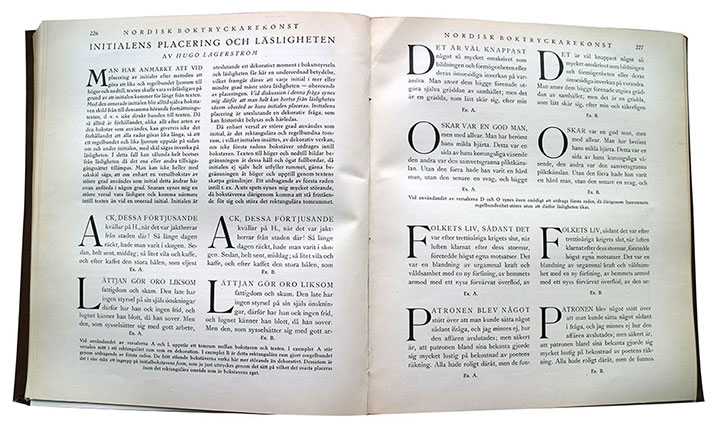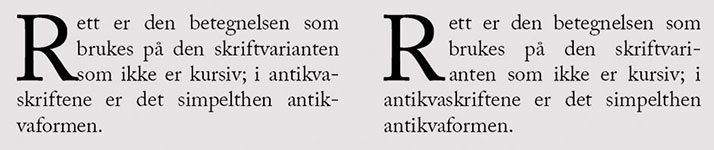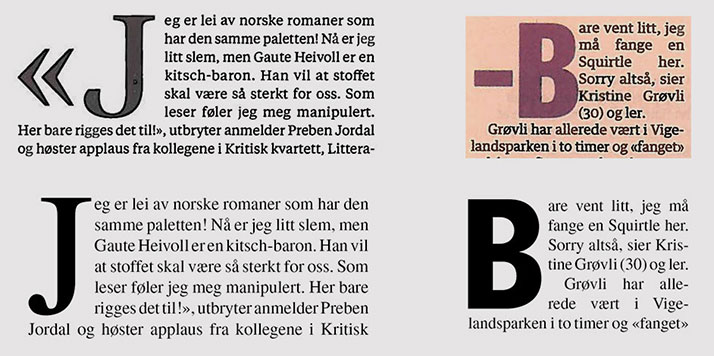
Initialer har vært anvendt i bøker lenge før Gutenberg og boktrykkerkunsten. De var ofte små malte kunstverk i de håndskrevne bøkene. Også i de første trykte bøkene ble disse utført for hånd av egne kunstnere eller håndverkere. Etter hvert ble det brukt typemateriell til initialer. Da oppsto det tvil om hvordan initial og tekst skulle knyttes sammen på en funksjonell og estetisk god måte.
Denne artikkelen vil ikke drøfte alle de vurderingene man kan gjøre seg om den typografiske formgivingen av initialer – også kalt begynnelsesbokstaver. Jeg har interessert meg for ett snevert forhold: hvordan initialen skal knyttes til resten av ordet/teksten som den tilhører. Skal den første linja trekkes nærmere initialen enn de etterfølgende? Jeg vil ta utgangspunkt i en strid i svensk boktrykkermiljø om dette omkring år 1920, der også praksisen i norsk boktrykk ble brakt inn i debatten.
Betydningen av dette spørsmålet vil noen avfeie som lite viktig, som «strunt» som noen uttrykte det i den svenske debatten. Og det er da lenge siden 1920? Men fortsatt er det ulike syn og ulik praksis vedrørende denne detaljen. Spørsmålet om plasseringen av initialer illustrerer hvilke hensyn man bør ta for å oppnå god leselighet og form, og hvilke virkemidler typografien har til rådighet. Temaet er dessuten aktualisert av de automatiske løsningene for å generere initialer i dagens grafiske produksjonsprogrammer: er de gode nok, og kan de brukes? – Men ja: det er andre, mer irriterende problemstillinger ved dagens bruk av initialer enn dette, og noen av disse vil jeg nevne til slutt.
Boktrykkets barndom
De første boktrykkerne satte av et tomt, firkantet område for initialen i satsen. Her skulle den påføres for hånd, ved maling eller kalligrafi. Etter hvert begynte boktrykkerne å bruke typemateriell som initial, og denne var en integrert del av satsen. De fortsatte å la initialen fylle et firkantet felt, slik at det var lik avstand til initialen for alle linjene på høyre side av initialen. Typemateriellet var i denne perioden ofte en spesielt utformet initialtype, en bokstav på en firkantet dekorert bunn.
Det var vanlig at det første ordet etter initialen (eller de første ordene) på den etterfølgende linja var satt med versaler (store bokstaver) eller med kapitéler (versaler på høyden til små bokstaver av typen n og x). Trolig var hensikten med dette å knytte initialen gjennom dens versalform til versalbokstaver i den første linja.
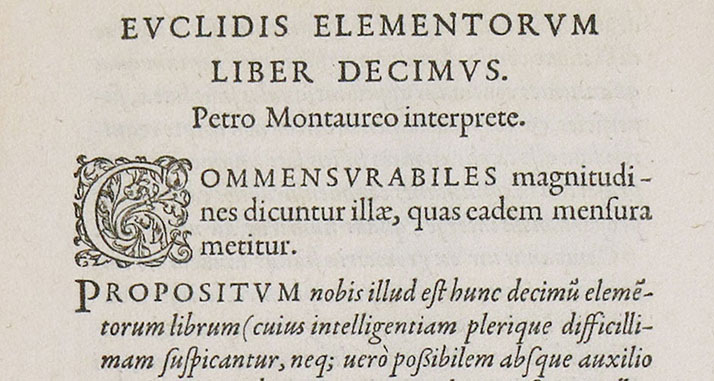
Dekorert initial med etterfølgende ord satt med store bokstaver, uten sammenbinding til initial. Euclids Elementorum liber decimus trykt av Michel de Vascosan i Paris 1551.
På et tidspunkt må noen ha begynt å tenke at initialen bør knyttes enda tydeligere til det ordet den tilhører, altså til den første linja. Enkelte boktrykkere lot derfor de etterfølgende linjene rykke lenger fra initialen, slik at den første linja fikk en nærmere tilknytning enn de øvrige linjene.
Det var om dette initialstriden sto i Sverige 1919–1921. Boktrykker Waldemar Zachrisson i Göteborg, utgiver av fagbokserien Boktryckeri-kalender, mente at nærheten mellom initial og første linje var «så axiomatisk riktig att därom icke behövde diskuteras». Men boktrykker Hugo Lagerström i Stockholm, utgiver av fagbladet Nordisk boktryckarekonst, hadde fått et annet syn på saken. Initialens dekorative funksjon var viktigst, mente han, det var derfor den ble brukt, så lesbarheten var nødvendigvis underordnet. En lik avstand til teksten både under og til høyre for initialen var det estetisk beste for initialens dekorative hensikt.
Temperaturen i diskusjonen var høy, og også andre debattanter lot sin mening høre i Nordisk boktryckarekonsts spalter. Det var 15 innlegg om temaet i 1920-årgangen.
Autoritetenes syn
Begge sider påberopte seg støtte i historien og hos autoriteter. Lagerström viste til at hans syn var helt dominerende i boktrykkerkunstens første århundrer, hos de beundrede boktrykkerne Ratdolt, Manutius, Plantin og andre. Han argumenterte med at ved å ha lik avstand mellom initialen og teksten blir satsen mer rolig, fast og regelmessig. Han mente at praksisen der den første linja sammenbindes med initialen kom med boktrykkets nedgangsperiode på 1800-tallet.
Zachrisson derimot støttet seg på en lang rekke fagbokforfattere, som svenske Nordin, amerikanske de Vinne og danske Selmar. Disse var samstemte i å anbefale at den første linja skulle sammenbindes med initialen. Zachrisson mente at luften som oppsto rundt initialen var uheldig, og sammenlignet den med de beryktede «flodene» som kan oppstå i brødtekst når store ordmellomrom kommer nær hverandre i flere påfølgende linjer. Ved at den første linja sto nærmere initialen ble denne «floden» lukket, mente han.
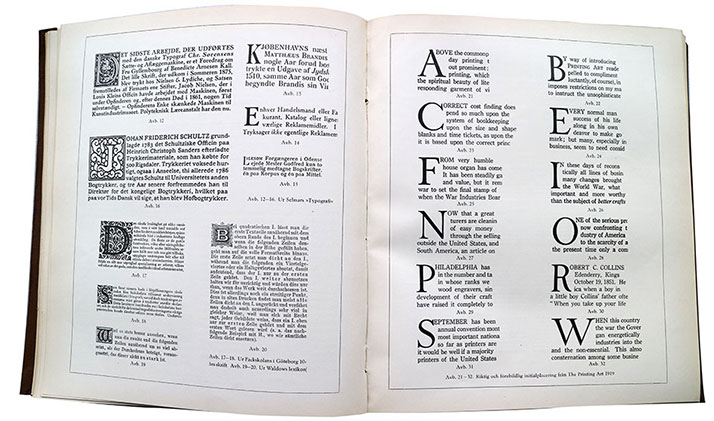
Et oppslag fra Zachrissons artikkel i Nordisk boktryckarekonst, fjärde häftet, april 1920. Han hadde til sammen 44 illustrasjoner i sin artikkel.
Men for Zachrisson var likevel hensynet til leseligheten viktigst. Han mente at de første boktrykkerne ikke alltid hadde lagt vekt på dette, mens det i våre dager var essensielt. «En initial skall och måste för läslighetens skull alltid bindas vid det ord den tillhör», skrev han. Lagerström besvarte dette med at initialens funksjon var dekorativ, og ved å bruke initialer hadde man uansett «offrat tydligheten för prydligheten». Og leseligheten ble minst forstyrret når initialen «placeras så att den lugnt och fast inställes i det kvadratiske utrymmet med lika, symmetriskt, ljusrum framtill som nedtill.».
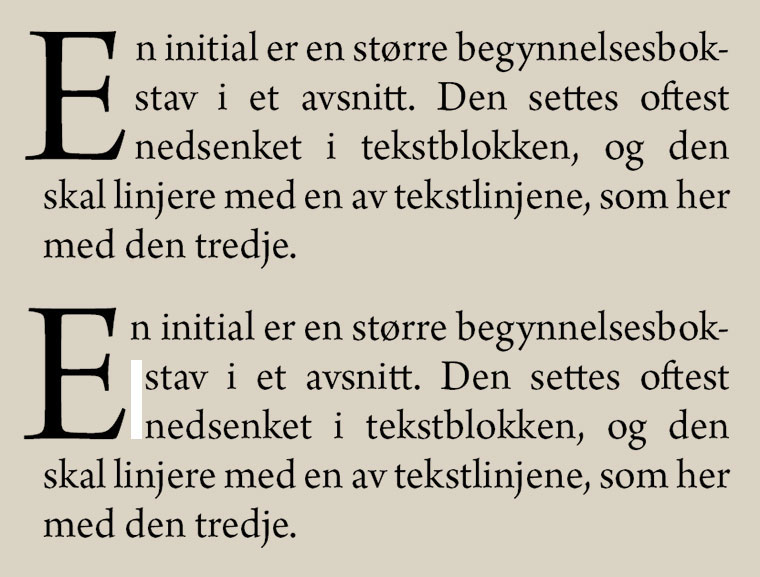
INITIALEN OG TEKSTEN
Skal initialen sammenbindes med første etterfølgende linje, som den jo tilhører, slik det nederste eksemplet viser? Eller er eksemplet øverst, der alle linjene har samme avstand til initialen, det beste, og naturlig å velge i og med at det er enklest å utføre? Det har vært ulik praksis og ulike synspunkter på dette gjennom typografiens historie. Diskusjonen tilspisset seg i en faglig debatt i Sverige i 1920. (Den hvite streken i eksemplet viser forskjellen på de to løsningene. Skrifttypen er Arno Regular – med initialen i Arno Display-snittet, som er magrere og mer elegant enn brødskriften. Teksten er hentet fra Christer Hellmarks Typografisk håndbok.)